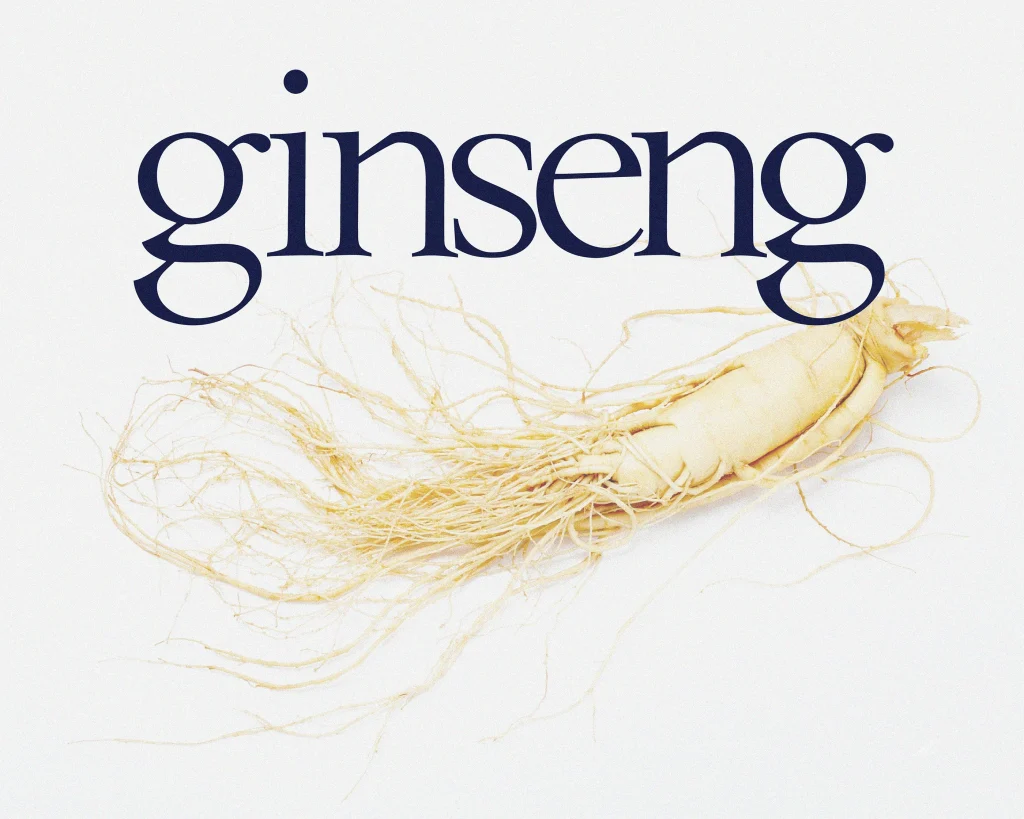
Williwaw Book
在当下大量几何无衬线与高对比现代衬线字体占据视觉主流的环境中,带有传统书卷气息的 Old Style(旧式衬线)字体依然拥有不可替代的魅力。Williwaw Book正是一款兼具古典气质、优雅比例与良好阅读性的免费英文字体,由美国设计师 Stephen T. French 于 2017 年发布,并明确授权个人与商业用途均可免费使用。对于需要营造文学感、品牌感与高级阅读体验的设计项目而言,这款字体提供了一种克制而耐看的视觉选择。
从官方字样与排版样张可以看出,Williwaw Book属于典型的 Old Style Serif(旧式衬线体)。它并不追求 Didot、Bodoni 那种极端高对比与强烈时尚感,而是延续了传统书籍排版中的温和结构与自然节奏。字体采用低至中等的笔画对比,粗细变化柔和,长时间阅读更加舒适;字母内部带有轻微的倾斜应力轴,保留了传统书法与金属活字时代的人文气息;衬线与主笔画之间的连接自然流畅,不显生硬。尤其是小写 a、g、y 以及 w 的曲线处理,能够明显感受到设计师对经典英文字体比例与节奏的细致研究。
在视觉表现上,Williwaw Book 的字面比例偏修长,整体气质优雅而安静。大写字母端庄克制,适合用于品牌标题、杂志封面和海报主视觉;小写字母则拥有较高的识别度与良好的阅读节奏,即使在中等字号下也能保持清晰稳定的表现。数字与标点符号的设计也延续了统一的衬线风格,引号、括号、分号等细节处理完整,能够满足专业编辑排版的需求。官方样张中展示了从 50pt 到 133pt 的多种字号效果,字体在不同尺寸下都能保持稳定的结构与视觉均衡,说明它不仅适合展示标题,也具备一定的正文排版能力。
从实际排版效果来看,Williwaw Book 最吸引人的地方在于它能够同时兼顾标题与正文。大标题呈现出明显的文学感与高级感,而多栏正文排版时又不会因为装饰性过强而影响阅读流畅度。这种平衡使它特别适合用于书籍、散文集、诗集、独立出版物、杂志、画册、品牌故事、文化类海报以及作品集网站等场景。如果你的项目需要一种“有文化感但不过分复古、有高级感但不显距离感”的英文字体,Williwaw Book 会比常见的 Times New Roman 或 Georgia 更具个性与辨识度。
与其他常见免费衬线字体相比,Williwaw Book 的定位也非常清晰。它不像 EB Garamond 那样偏向学术与长篇阅读,也不像 Cormorant 那样强调高对比与华丽感,而是介于两者之间,既保留了 Garamond 的人文阅读性,又吸收了一部分现代编辑字体的优雅气质。这种适中的个性使它在品牌设计、出版设计与数字内容排版中拥有更高的通用性。
总体来看,Williwaw Book 并不是一款追求强烈视觉冲击的“网红字体”,它真正的价值在于克制、耐看与长期可用。Stephen French 通过温和的笔画对比、传统的人文字母结构以及优秀的排版节奏,让这款字体在标题、正文与编辑场景之间取得了难得的平衡。对于独立品牌、文化内容创作者、杂志编辑以及注重细节的视觉设计师来说,Williwaw Book 是一款值得长期收藏和使用的免费可商用英文字体,它既保留了旧式衬线字体的温度,也具备现代数字排版所需的清晰度与稳定性。